Cuidar la presentación en Instagram es fundamental para cualquier creativo. Por ello, te enseñamos cómo modificar el tipo de letra de tu biografía de una forma muy sencilla.
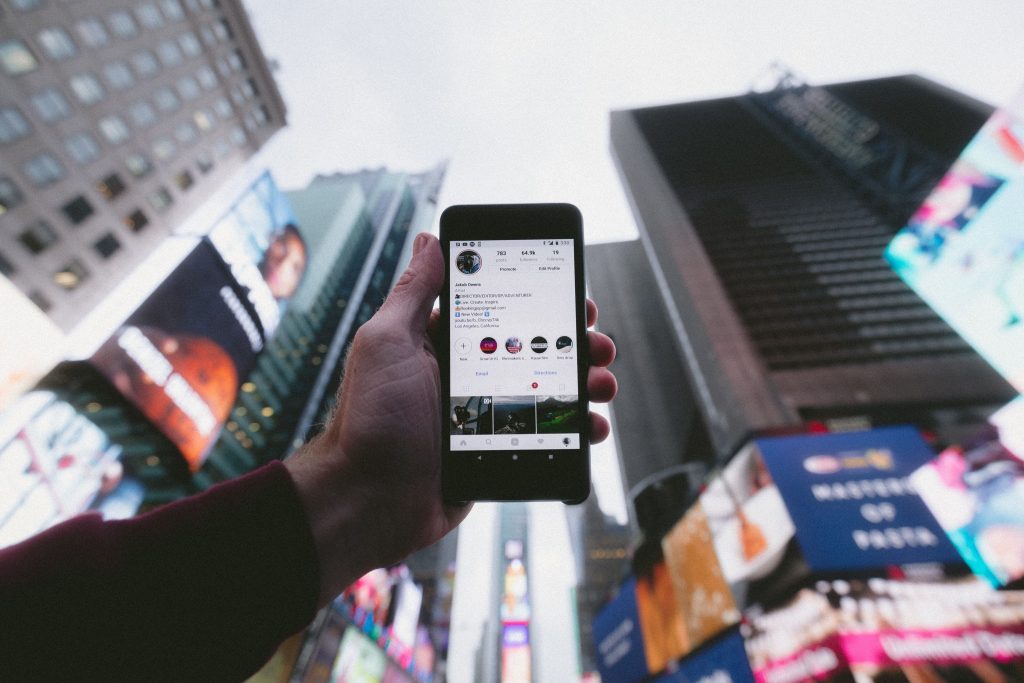
Cuidar los pequeños detalles en Instagram es imprescindible para cualquier creativo que quiera gustar a sus seguidores y conseguir potenciales clientes a través de esta red social. Para ello, debes tener en cuenta todas las funciones que Instagram te permite y plantearte todas las posibilidades. Una de ellas, que muchas veces pasa desapercibida, es la posibilidad de cambiar la tipografía predeterminada de Instagram en tu biografía.
Como Instagram, por ser eminentemente visual, es una de las principales plataformas para artistas y diseñadores, es lógico que quieras que tu biografía destaque, y el uso de una tipografía original puede ayudarte a conseguirlo. Pero tampoco debes elegir una tipografía infantil, así que dedica algo de tiempo a elegir el tipo de letra adecuado.
Si necesitas algo de inspiración, puedes consultar nuestras recomendaciones de tipografías gratuitas para ayudarte a decidir el tipo de letra. También puedes completar tu biografía con emojis que te ayuden a romper el hielo y añadir un poco de personalidad y color, pero tampoco te pases… Es importante que no sea difícil de leer.
También tienes que tener en cuenta que la modificación de tu biografía de Instagram implica el uso de un tipo de caracteres que no siempre se pueden ver en algunos dispositivos, por lo que es importante que no toda tu biografía tenga una fuente diferente. Por ello, la mayoría de gente sólo utiliza el cambio de fuente para su nombre, o una pequeña parte de su definición.
Cómo cambiar el tipo de letra de la biografía
Para modificar el tipo de letra primero tienes que abrir una herramienta generadora de fuentes para Instagram. Hay muchas disponibles en la web como por ejemplo Insta Fonts, Fancy Fonts, Instagramfonts o Messletters, entre muchas otras.
Escribe o pega el texto que quieres cambiar en el cuadro donde figura «Editar texto». A continuación, verás una lista de fuentes que se pueden utilizar en Instagram, y cómo se vería tu texto en cada una de ellas. Entre estas fuentes hay algunas que serán las adecuadas para tu biografía y otras serán casi imposibles de leer. Una vez que hayas encontrado la fuente que te convenga, utiliza el botón «Copiar» para copiar el texto.
Cuando hayas copiado el texto abre Instagram y haz clic en en botón de «Editar perfil». En el formulario que aparece pega tu texto en la casilla correspondiente. Si no te gusta el resultado final puedes volver fácilmente al primer paso y elegir otra.